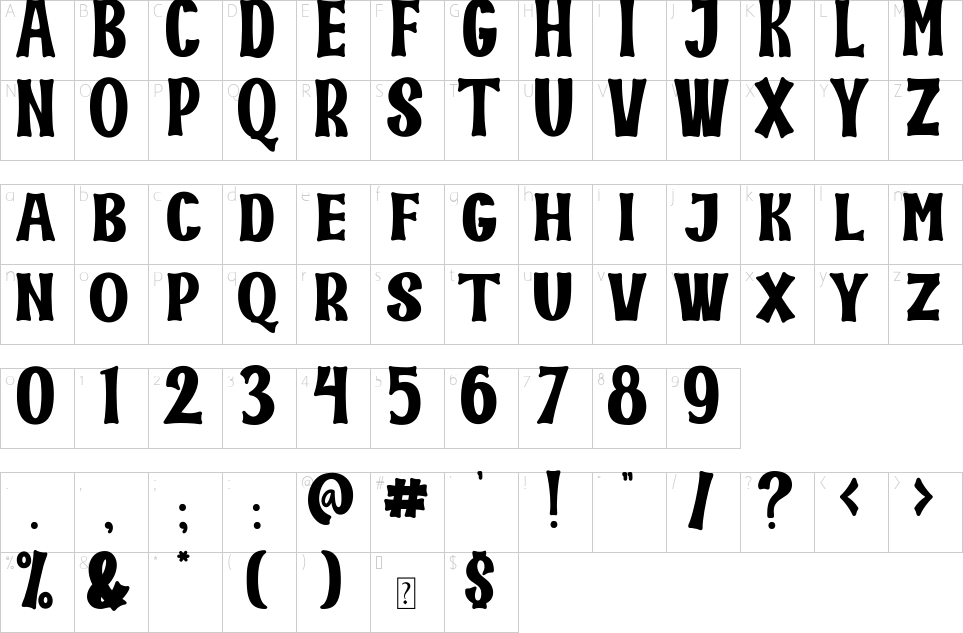
Dragon Kids Font – Fonte Grátis
Dragon Kids Font
Descubra a encantadora ‘Dragon Kids Font’, uma escolha perfeita para quem busca uma fonte infantil com estilo vibrante. Desenvolvida por StringLabs, esta fonte apresenta um design leve e encantador, ideal para aplicativos de crianças ou projetos educacionais. As linhas arredondadas e o tom suave garantem que qualquer texto seja facilmente legível, mesmo em páginas menores. Com seu download fácil e rápido, a ‘Dragon Kids Font’ oferece uma maneira linda e divertida de incorporar um pouco de magia no design das suas produções digitais. Se você está procurando por uma fonte de criança que se destaca com estilo único, esta deve ser sua escolha. Sinta-se convidado a explorar e experimentar o encanto da ‘Dragon Kids Font’.